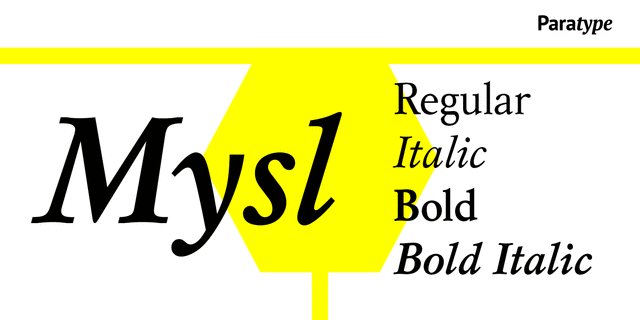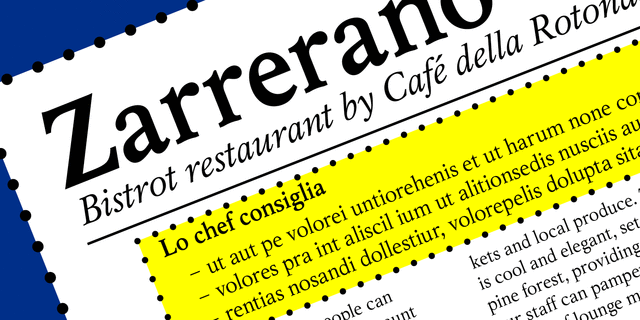
Mysl (4 шрифта)
Опис гарнітури MyslШрифт разработан в Отделе наборных шрифтов НПО Полиграфмаш в 1986 году (дизайнеры Исай Слуцкер, Светлана Ермолаева, Эмма Захарова) на основе рисунков гарнитуры Политиздатовская, 1966 год (дизайнер Вера Чиминова), по мотивам шрифтов французского пуансониста середины XVI века Клода Гарамона. Первоначально разрабатывался для московского издательства «Мысль». Применяется для текстового набора.